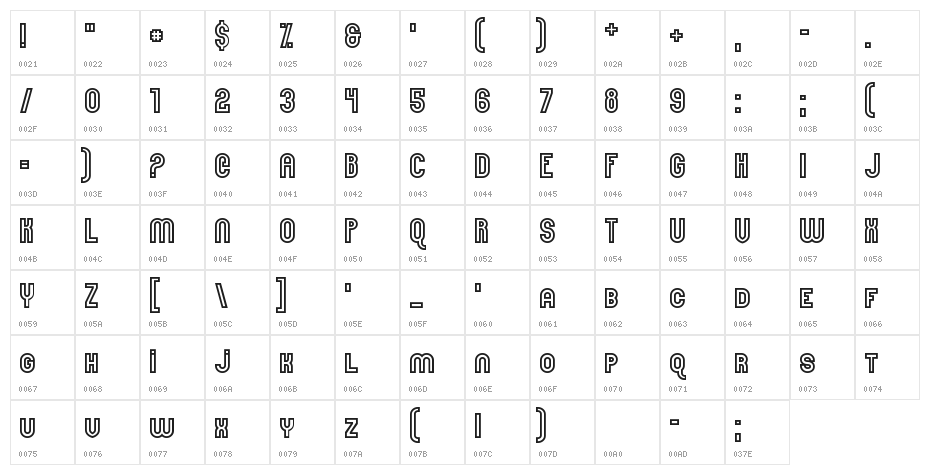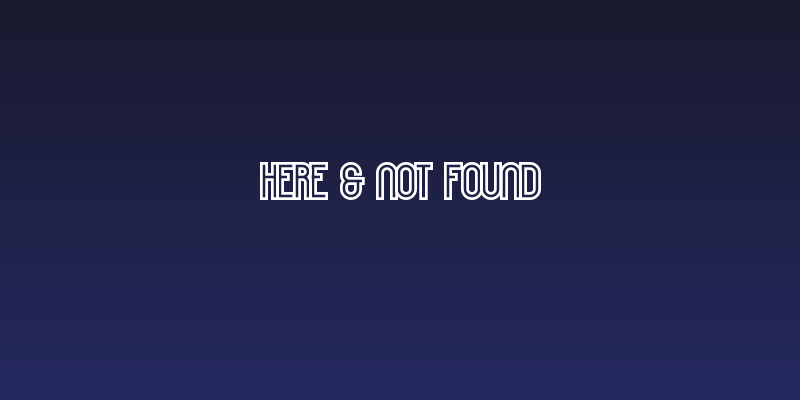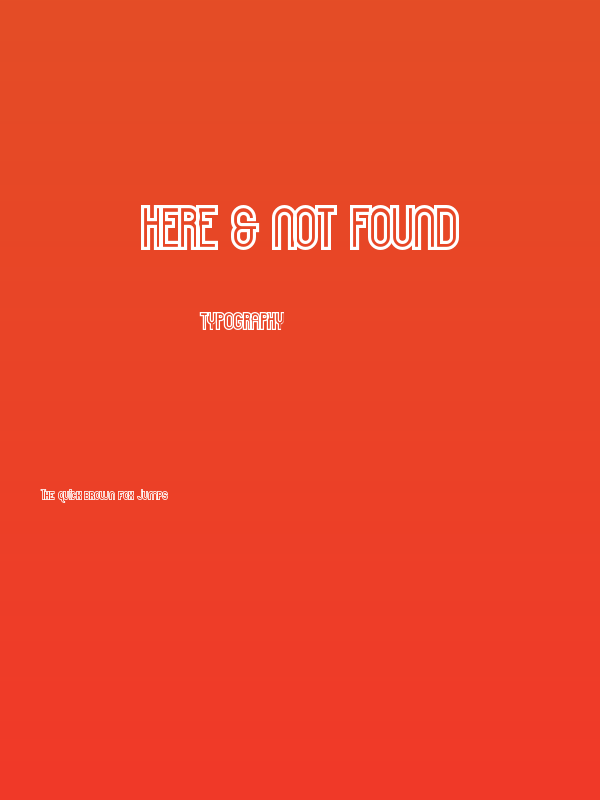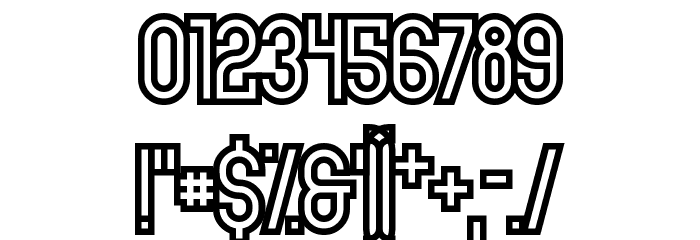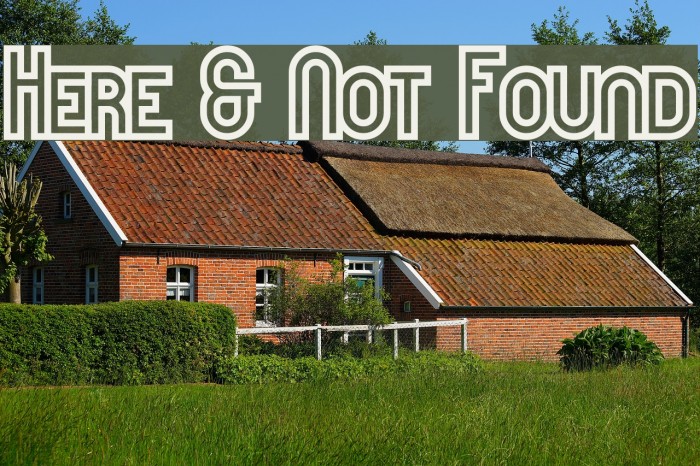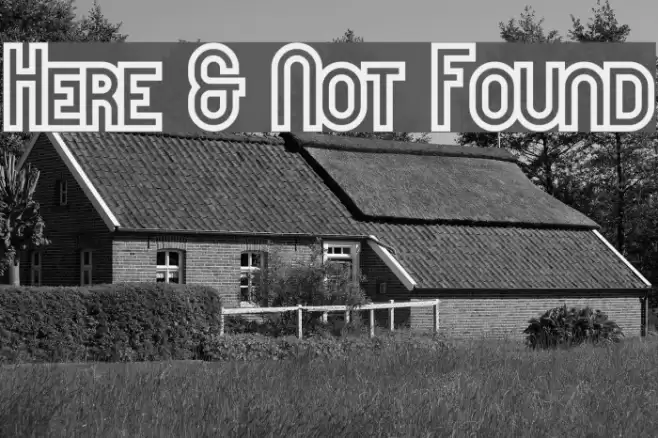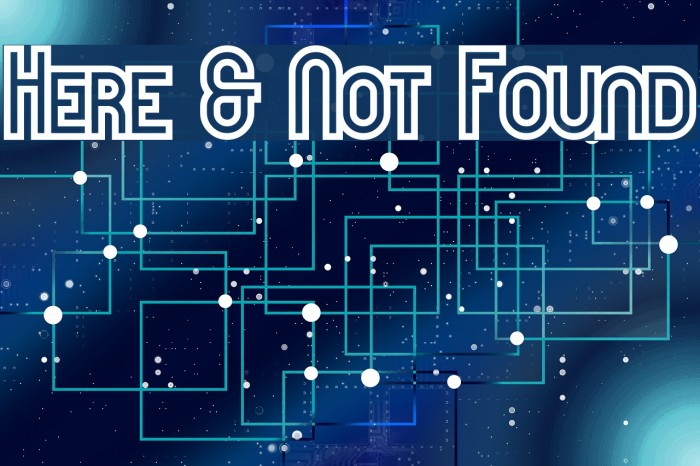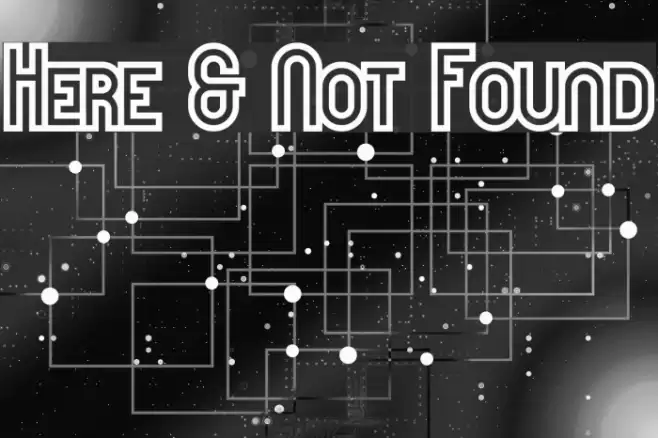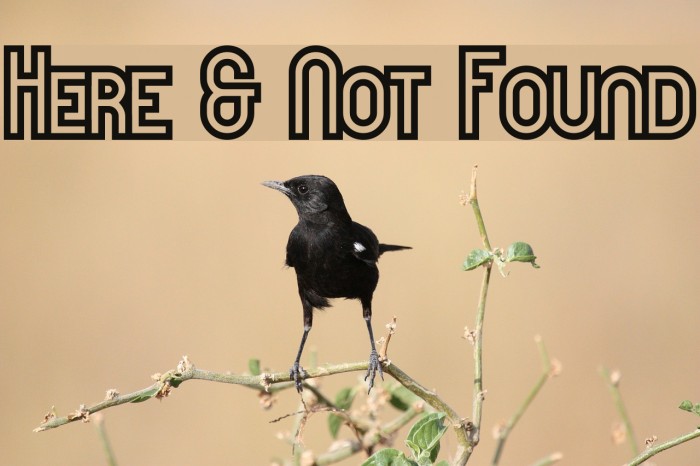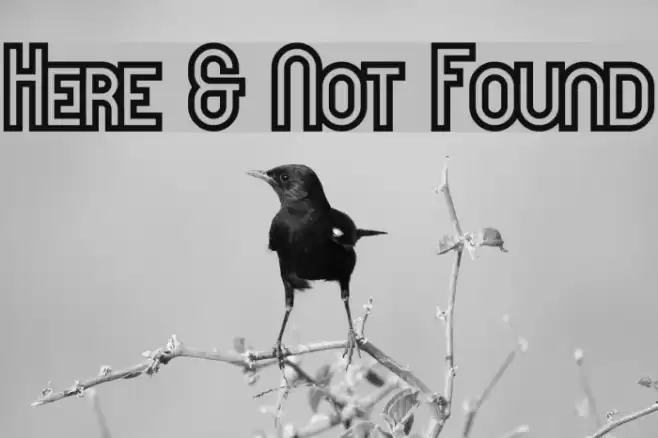
Here & Not Found Font
| Projetos propostos | This font is perfect for poster designs, branding projects, and any creative work that requires a strong visual impact. It can also be used effectively in digital media, such as website headers and social media graphics. |